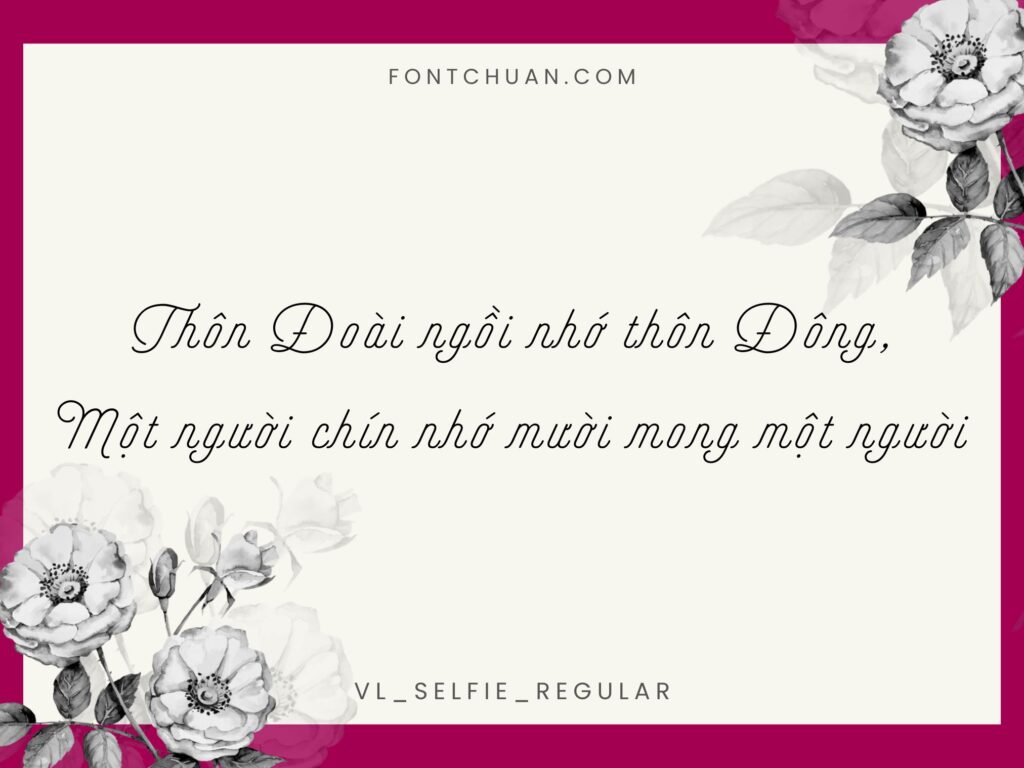
Font VL Selfie Việt Hóa
VL-Selfie-Regular là một phông chữ script mang phong cách thư pháp hiện đại, nổi bật với các đường nét mềm mại và uyển chuyển. Được thiết kế bởi Maximiliano R. Sproviero, phông chữ này kết hợp giữa cổ điển và hiện đại, phù hợp cho nhiều mục đích sử dụng như thiết kế thiệp mời, poster, logo và tiêu đề sách. VL-Selfie-Regular đã được Việt hóa bởi Việt Linh, hỗ trợ đầy đủ các ký tự tiếng Việt, giúp người dùng tại Việt Nam dễ dàng áp dụng trong các dự án sáng tạo. Phông chữ này được thành viên Font Chuẩn sưu tầm và đăng tải nhằm phục vụ nhu cầu thiết kế đa dạng.
Với thiết kế duyên dáng và linh hoạt, VL-Selfie-Regular phù hợp cho các ứng dụng như thiệp mời, poster, logo và tiêu đề sách. Trong lĩnh vực sự kiện, phông chữ này có thể được sử dụng trong các dịp như thiệp cưới, lễ hội và sinh nhật. Ngoài ra, VL-Selfie-Regular cũng thích hợp cho các ngành nghề như quảng cáo, ẩm thực, spa và ảnh cưới.